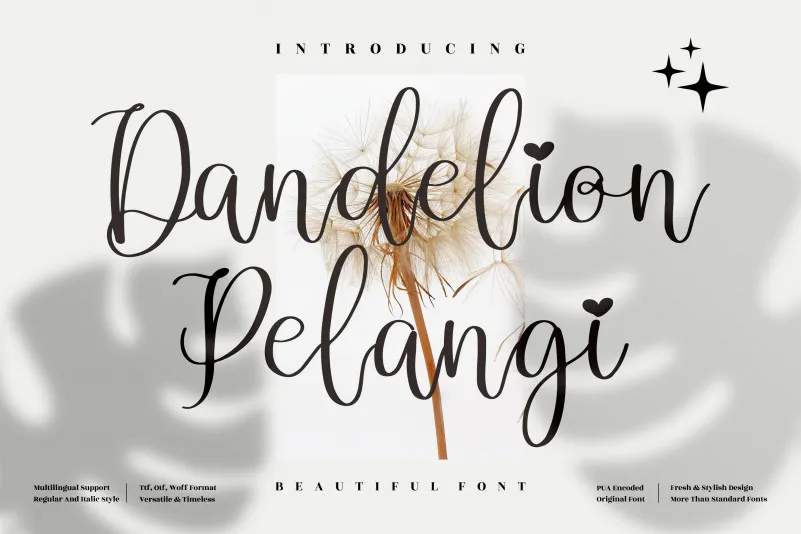
Dandelion Pelangi é uma fonte script que oferece um toque romântico adequado para uma variedade de projetos. Ideal tanto para elementos visuais como logos, branding, designs de produtos e embalagens, quanto para objetos pessoais como posters, camisetas e cards de convite. Suas linhas delicadas são perfeitas para criar mensagens agradáveis em diversos materiais, desde papel até metal. A Dandelion Pelangi se adequa com perfeição para qualquer projeto que busque um toque romântico e elegante no estilo da calligrafia. Esta fonte é a escolha ideal para quem busca um charme único em suas criações visuais.